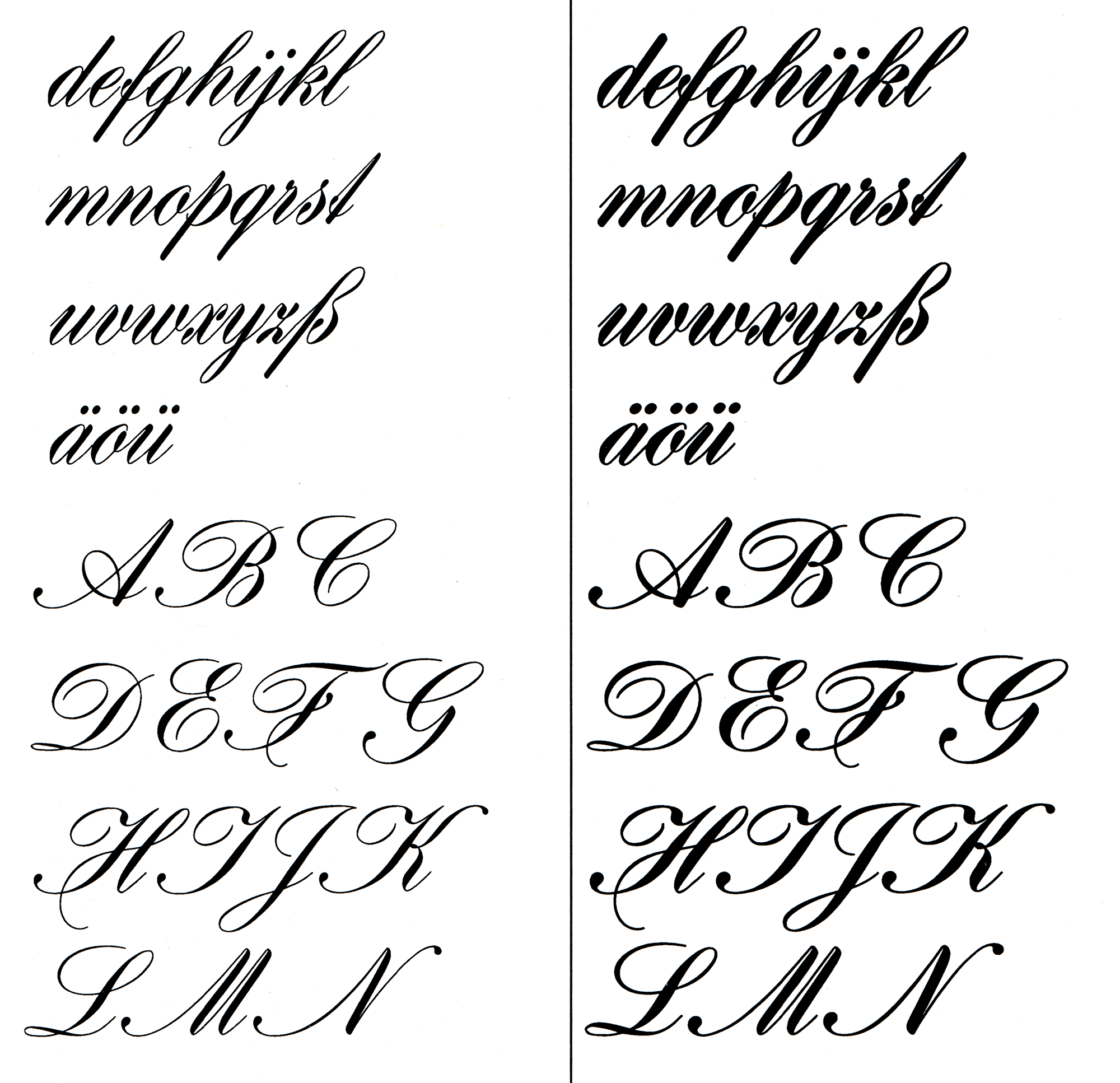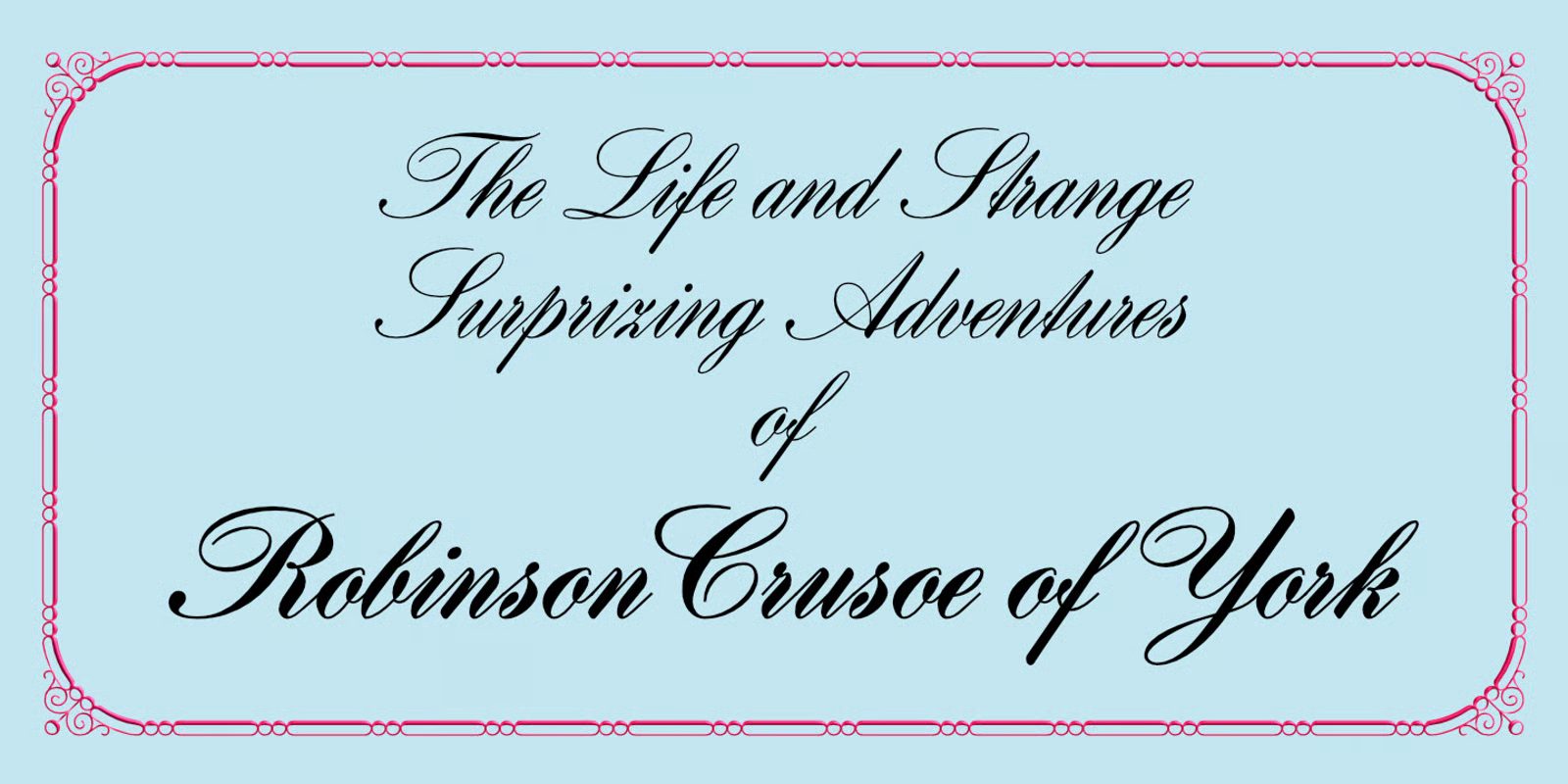
Font-Wiki: Hogarth-Script
• 1984
• Antiqua Schreibschrift
Die Hogarth-Script ist eine englische Schreibschrift, die von Harald Brödel als Fotosatzschrift für den VEB Typoart Dresden geschaffen wurde. Benannt ist die Schrift nach dem englischen Maler William Hogarth.
Es gab zwei Strichstärken (mager, halbfett) und die aktuelle Elsner+Flake-Umsetzung verweist auf drei Größenbereiche (TB, TD, TH). Darüber hinaus existieren Digitalisierungen anderer Anbieter, etwa URW++ (Hogarth Script) und RMU Fonts (Gillray Pro).
RMU-Version
Original-Fotosatz-Version